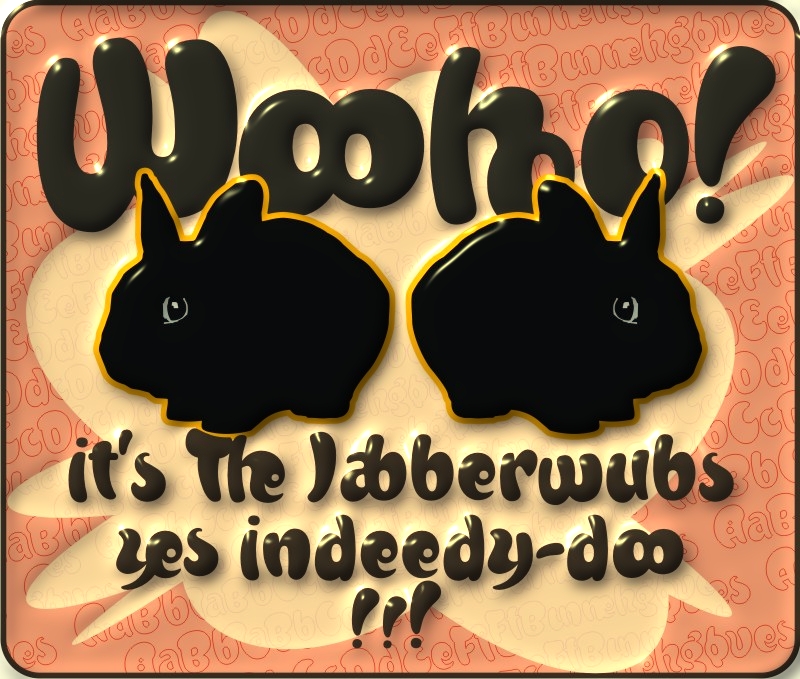
Also, die Frank Pro von gestern ist mit Sicherheit nichts für mich, auch wenn die Idee vielleicht ganz interessant ist. Aber diese hier finde ich ja irgendwie echt knuffig, auch wenn es davon vermutlich viele gibt:
A fresh new decorative display face bubbling with life & spontaneity, Jabberwub belongs to a rare genus of creature fonts that time forgotócasual animated. A fun & bouncy eye-catcher that crosses into the land of the zany, dancing a whacky line between discord & rhyme, Jabberwub packs tons of fun into a state-of-the-art OpenType font loaded with 270 extra glyphs, including stylistic alternates, discretionary ligatures, word ligatures and capitalized ligatures, allowing creative typographers to achieve a custom hand-lettered look without all the mess & spilt glue of a manual paste-up job. Just like using rub-down type but it never cracks or splits, and it never runs out. The moment you start using Jabberwub you'll be laffing!
Jabberwub is ideal for whatever zany stuff springs to mind. It takes an outline with no problem-o, and you can squish & squoosh it as the occasion takes your fancy. Optimal results are achieved by hand setting each individual glyph. Available in OpenType only.